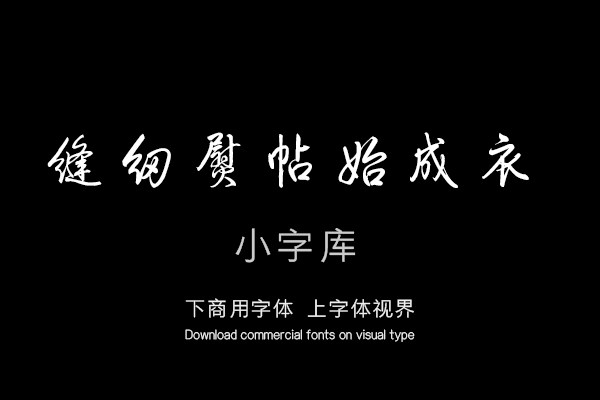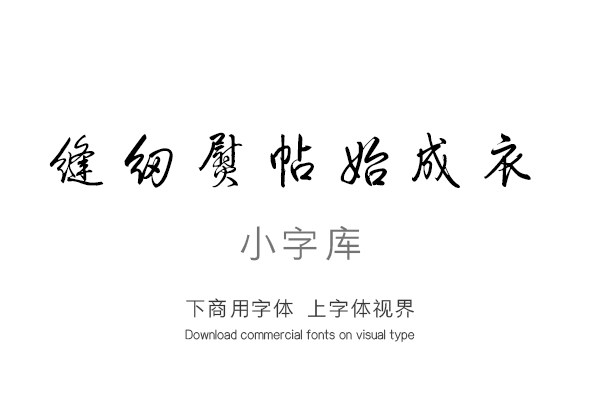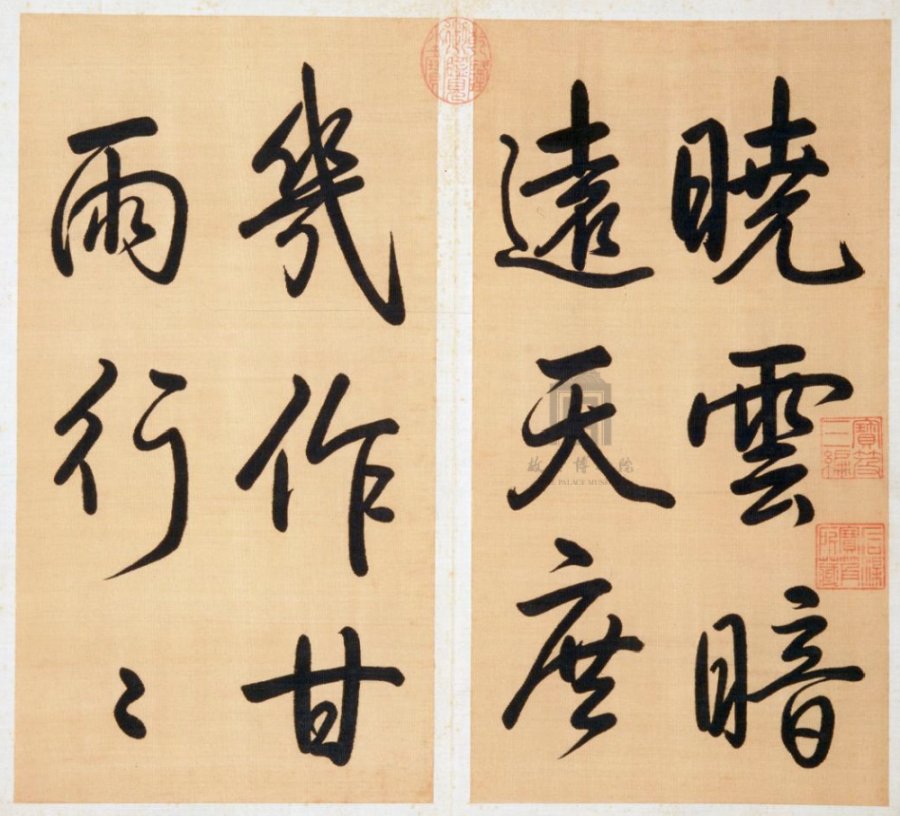
汉标乾隆晓云诗疋帛谣
《汉标乾隆晓云诗疋帛谣》是一款根据缂丝乾隆御笔泮池济宁行宫诗册(第十册)经过再次调整制作的小字库,该小字库共收录了该真迹作品中约184个字体。
《晓云诗》:   晓云暗远天,庶几作甘雨。   行行散以轻,失望意为抚。   结穗者垅麦,吐苗者坂黍。   胥待膏泽滋,吾民一何苦。   已近圣人里,敬忆圣人语。   秀而恐弗实,学与农同矩。   晓云一首 丙申 暮春月下浣御笔   《疋帛谣》:   戋戋彼疋帛,裁量用刀尺。   缝纫熨帖始成衣,一絲牵引万絲随。   古人制字有深意,至心如丝声从思。   子舆训官曰得之,大易又戒朋從来。   人心惟危道心微,试看一絲與万丝。   疋帛谣 丙申暮春下浣御笔